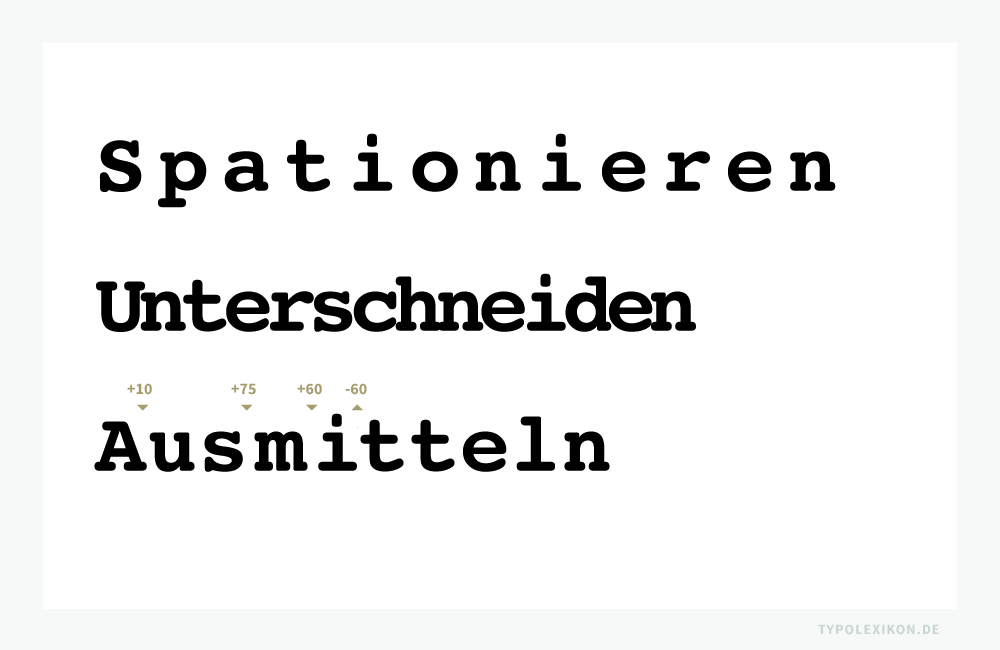
Optischer Schriftweitenausgleich
Typografischer Terminus für die Veränderung der Schriftlaufweite einer Druckschrift oder eines Screen Fonts; optische Korrektur der Schriftlaufweite einer Zeichenkombination, eines Wortes oder Textes durch eine positive (+LW) und/oder negative (-LW) Laufweitenveränderung; Laufweitenausgleich; Abk. »OSW«.
Der Optische Schriftweitenausgleich umfaßt folgende Methoden:
• Spationieren
Wird die Normalschriftweite (NSW) bei Proportionalschriften durch eine positive Laufweitenveränderung (+LW) erweitert, spricht man von »Spationieren«.
• Sperren
Wird der normale Breitenlauf physischer Drucktypen aus Metall (z.B. aus einer Blei-Zinn-Antimon-Kupfer-Legierung), Holz (z.B. aus Birnenholz) oder Kunststoff (z.B. aus Kunstharz) mit gleich großen Trennfugen bzw. Spatien erweitert, nennt man das »Sperren«.
Wird die Normalschriftweite bei Proportionalschriften durch Leerraumzeichen oder durch gleich große Leerraumgevierte erweitert, spricht man ebenfalls von »Sperren«.
Wird die Normalschriftweite bei Nichtproportionalschriften (dicktengleiche Schriften, Festbreitenschriften) mit Leerraumzeichen erweitert, bezeichnet man das als »Sperren« oder »dicktengleiches Sperren«.
• Unterschneiden 1)
Wird eine Schriftlaufweite bei Proportionalschriften grundsätzlich durch eine negative Laufweitenveränderung (-LW) verringert, wird das »Unterschneiden« genannt.
• Kerning
Wird bei Proportionalschriften der ästhetische Schriftweitenausgleich kritischer Zeichenpaare automatisch aufgrund einer Kerning-Tabelle unterschnitten, spricht man vom »Relativen Kerning«, »Automatischen Kerning« oder »Autokerning«.
Wird bei Proportionalschriften der Abstand zwischen zwei Zeichen durch eine manuelle negative Laufweitenveränderung (-LW) verringert, wird das als »Zeichenabstandskerning« bezeichnet.
Wird bei Proportionalschriften der Abstand zwischen zwei Worten durch eine negative Laufweitenveränderung (-LW) verringert, nennt man das  »Wortabstandskerning«.
• Ausgleichen
Werden innerhalb einer Zeichengruppe die Abstände individuell vergrößert (+LW) und verkleinert (-LW), um damit optisch einen gleichmäßigen Weißraum zu erzielen, wird dies als »Ausgleichen« oder »Ausmitteln« bezeichnet.
Optischer Schriftweitenausgleich (OSW). Obere Zeile: Spationierung der Normalschriftweite mit +140/1000 Geviert erweitert. Mittlere Zeile: Unterschneidung der Normalschriftweite mit -100/1000 Geviert verengt. Untere Zeile: Normalschriftweite mit +/-Geviertwerten ausgemittelt. Beispiel gesetzt mit Photoshop® von Adobe® in Courier bold von Apple (Systemschrift). Infografik: www.typolexikon.de
Optischer Schriftweitenausgleich (OSW). Obere Zeile: Spationierung der Normalschriftweite mit +140/1000 Geviert erweitert. Mittlere Zeile: Unterschneidung der Normalschriftweite mit -100/1000 Geviert verengt. Untere Zeile: Normalschriftweite mit +/-Geviertwerten ausgemittelt. Beispiel gesetzt mit Photoshop® von Adobe® in Courier bold von Apple (Systemschrift).
Motive
Es gibt unterschiedliche Argumente, die einen Optischen Schriftweitenausgleich rechtfertigen können:
Spationieren
Sperren
• Optimierung der Schriftsatzästhetik, beispielsweise von Ruftext, Kolumnentiteln, Kapitälchen oder Majuskeln.
• Sperrsatz in der Schriftgattung der Gebrochenen Schriften.
• Auszeichnung bei mechanischen Schreibmaschinen.
• Dicktengleiches Tabulieren im Tabellensatz oder Programmlisting.
Unterschneiden und Kerning
• Optimierung der Schriftsatzästhetik durch negative Laufweitenveränderung (-LW), beispielsweise bei sehr großen Headlines, insbesondere bei sehr großen Majuskeln.
• Optimierung der Schriftsatzästhetik durch negative Laufweitenveränderung (-LW) bei Unterschneidungspaaren, z.B. bei Av, AV, Aw, AW, LT, LV, Ly, Ta, Te, To, Ty, T., Va, Vo, V., Ya, Yo oder Y.
• Negative Laufweitenkorrektur (-LW) einer fehlerhaften, zu weiten Normalschriftweite, um die Lesbarkeit der Schrift zu erhöhen.
• Negative Laufweitenveränderung (-LW) bei Werksatzschriften bzw. Textschriften in Schaugrößen, Ferngrößen und Plakatgrößen, um Texte in sehr großen Schriftgraden besser lesbar zu machen.
• Selektive negative Laufweitenveränderung (-LW) als mikrotypografische Verfahrensweise, um eine Zeile, einen Tabellensatz oder eine Zahlenkombination auszutrimmen.
• Selektive negative Laufweitenveränderung (-LW) als Korrektur von zu großen Wortzwischenräumen.
Ausgleichen
• Optimierung der Schriftsatzästhetik durch positive (+LW) und negative (-LW) Laufweitenveränderung, um die Weißräume innerhalb von Zeichengruppen bei Proportionalschriften ästhetisch anzupassen, z.B. bei Majuskeln, Kapitälchen, Römischen Zahlen, Mediävalziffern oder im Titelsatz.
↑1 Anmerkung: Mit der Etablierung des optomechanischen Lichtsatzes (Fotosatz) seit Anfang der 1960er Jahre hat der Anglizismus »Kerning« sukzessive die deutschen Fachbegriffe »Zurichtung« und »Unterschneidung« in Teilen ergänzt oder ersetzt, wobei der Begriff »Kerning« im Detail unterschiedlich interpretiert werden kann.